Stellen Sie sich das vor: Sie entwerfen eine Nachricht, kraftvoll und präzise, doch die Schriftart ist es, die wahre Bände spricht.
Als Webdesigner habe ich mich durch die komplexe Welt der Typografie navigiert, wo die richtige Schriftwahl zum unbesungenen Helden der Klarheit wird, insbesondere im Bereich kleiner Text.
In diesem ausführlichen Bericht erforschen wir die besten Schriften für kleinen Text, eine Reise, die Ihr Typografie-Design von übersehen zu herausragend verwandeln wird.
Schriften sind nicht nur Buchstaben; sie sind stille Botschafter Ihrer Nachricht. Haben Sie sich jemals die Augen über Kleingedrucktes angestrengt oder an einem digitalen Bildschirm die Augen zusammengekniffen? Es ist ein universeller Kampf, und hier gehen wir ihn direkt an.
Von der Lesbarkeit winziger Schriften bis zu den optimalen Schriftarten für Kleingedrucktes werden wir die Geheimnisse hinter der Schriftklarheit in winzigen Größen enthüllen.
Ob Sie Designer, Marketingfachmann oder einfach schriftneugierig sind, Sie werden die Magie von Schriftarten wie Sans-serif und Serif entdecken und wie sie selbst in kleinsten Räumen Macht ausüben.
Die besten Schriften für kleinen Text
| Schrift | Lesbarkeit bei kleinen Größen | Designstil | Verwendungskontext |
|---|---|---|---|
| Open Sans | Hervorragend | Sans-serif | Web, Druck, UI |
| Source Sans Pro | Hervorragend | Sans-serif | Web, Druck, UI |
| Ubuntu | Gut | Sans-serif | Web, Druck, UI |
| Lipa Agate | Gut | Serif | Zeitung, Kleine Etiketten |
| Solente | Durchschnittlich | Serif | Redaktionell, Druck |
| Focus Grotesk | Gut | Sans-serif | Branding, Redaktionell |
| Numhead Typeface | Ausreichend | Slab-serif | Display, Branding |
| Edit Small | Hervorragend | Sans-serif | Web, UI, Kleiner Text |
| Manurewah | Durchschnittlich | Handschriftlich | Lässig, Einladungen |
| Canterbury | Schlecht | Fraktur | Überschriften, Dekorativ |
| Brock Script | Ausreichend | Schreibschrift | Einladungen, Überschriften |
| Sacramento | Ausreichend | Schreibschrift | Überschriften, Display |
Empfohlene Schriften für kleinen Text
Serifenschriften
Also lassen Sie uns in die Welt der Serifenschriften eintauchen. Diese Typen sind wie die klassischen Vinyl-Schallplatten der Schriftwelt – zeitlos, stilvoll und sie heben alles, was sie berühren, auf eine höhere Ebene. Und wenn es um die besten Schriften für kleinen Text geht, stechen einige Serifenschriften wirklich hervor.
Zuerst haben wir BD Megalona Text Serif Font Family. Diese Schrift ist wie dieser Freund, der alles gut kann. Sie hat eine ordentliche Balance, was sie perfekt für kleinen Text macht. Und es geht nicht nur darum, gut auszusehen; es geht darum, lesbar zu sein, selbst wenn Sie auf winzigen Druck starren.
Dann gibt es Magnita – Serif Small Letter Font. Diese Schrift ist ein wenig wie ein feiner Wein – sie wird bei jedem Blick besser. Speziell für kleine Größen entworfen, bewahrt sie Eleganz ohne Lesbarkeit zu opfern. Sie ist eine erste Wahl für Projekte, bei denen Sie eine edle Note verleihen möchten, ohne Ihr Publikum in einem Meer von undeutlichen Buchstaben zu verlieren.
Haben Sie schon von Rodian – Serif Web Font Small Size gehört? Stellen Sie sich vor: Sie erstellen eine Webseite und benötigen Text, den Besucher lesen können, ohne nach ihren Brillen zu greifen. Rodian tritt in Aktion. Er ist für das Web gebaut und stellt sicher, dass sogar der kleinste Call-to-Action kristallklar ist.
Edita Small andererseits, ist ein Traum für Buch- und Magazinliebhaber. Wenn Sie durch Seiten blättern, möchten Sie eine Schrift, die mühelos fließt. Edita Small macht genau das, durch lange Lesezeiten ohne Anstrengung.
Dann geht es weiter zu Morjuis – Elegante Serifenschrift für kleine Textprojekte. Diese Schrift ist wie das Sahnehäubchen auf einer Eistüte. Sie fügt jedem Projekt eine elegante Note hinzu und macht kleinen Text nicht nur lesbar, sondern auch absolut hinreißend.
Zuletzt in dieser Kategorie, aber sicher nicht zuletzt, ist Runalto – Luxus-Serifenschrift. Es ist, als würde man einen maßgeschneiderten Anzug anziehen – es fühlt sich einfach richtig an. Diese Schrift verleiht Ihrer Arbeit einen klassischen Look und macht jedes Wort ein wenig spezieller.
Sans-Serif-Schriften
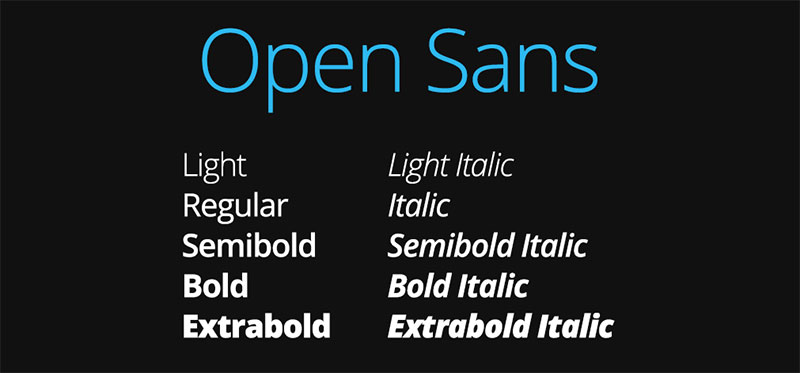
Jetzt wechseln wir zu Sans-Serif-Schriften. Diese sind die modernen, schlanken Sportwagen der Schriftwelt. Sie sind klar, sie sind prägnant, und sie bringen eine zeitgemäße Atmosphäre mit.
An erster Stelle steht Cora – Extra große x-Höhe für Klarheit. Diese Schrift ist ein Lebensretter, wenn Sie mit kleinem Text arbeiten. Die extra große x-Höhe bedeutet, dass jeder Buchstabe hervorsticht, was den Text lesbar macht, selbst wenn er wirklich klein ist.
Numhead Typeface ist wie die techno-industrielle Musik der Schriften – es hat diesen kantigen, modernen Look, der einfach bei technischen oder futuristischen Projekten passt. Es ist perfekt, wenn Sie eine Aussage machen möchten, ohne dass Ihr Text untergeht.